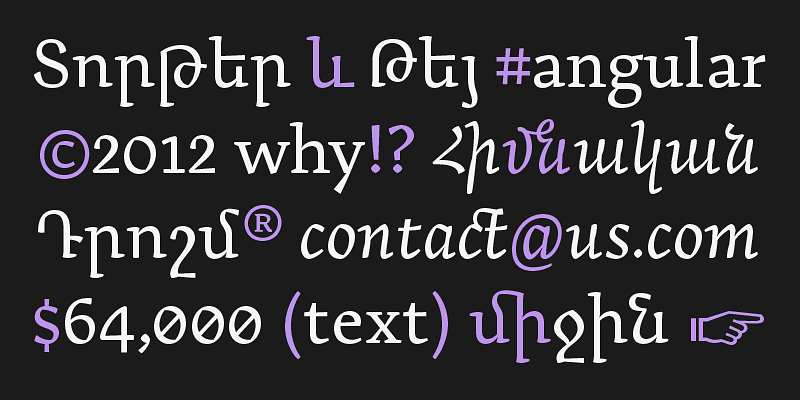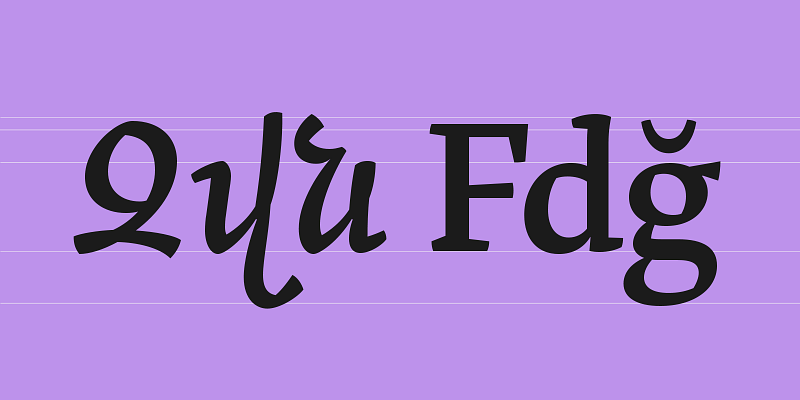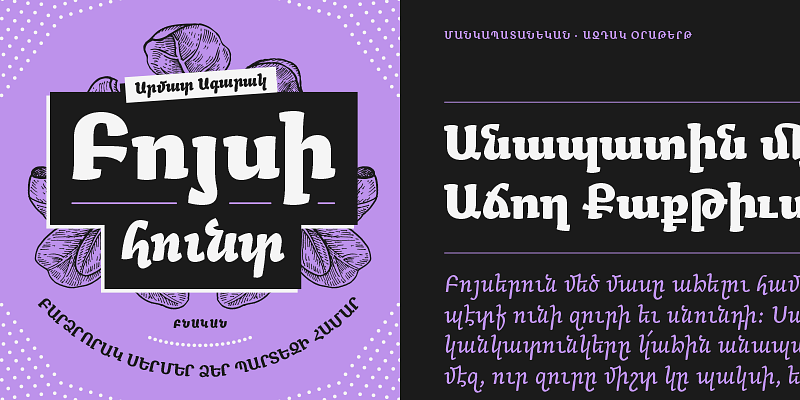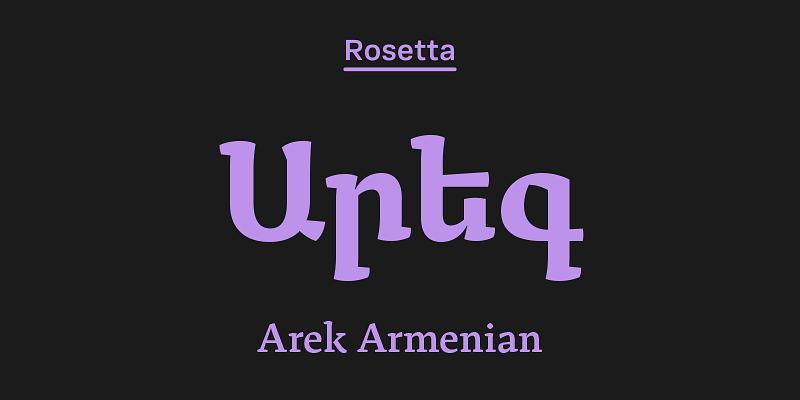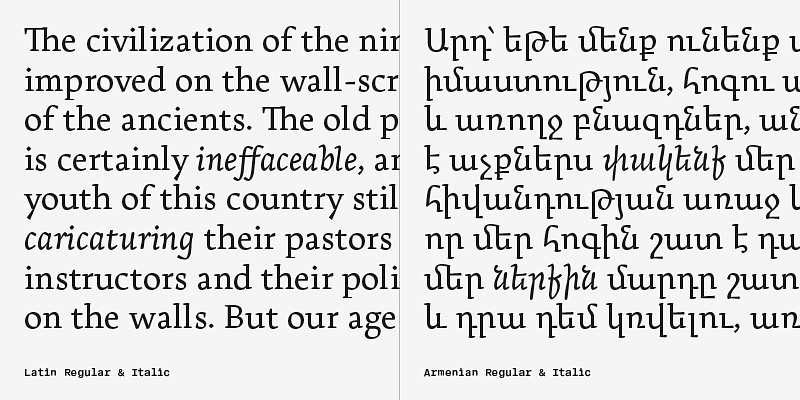
Arek ist eine leistungsstarke Sammlung von Schriftfamilien mit mehreren Strichstärken. Sie kombiniert eine klare, gut lesbare Hochkantschrift mit einer innovativen armenischen Kursivschrift und einer passenden lateinischen Schrift, die sich die Seite harmonisch teilen. Ursprünglich wurde Arek für Schulbücher entwickelt, aber auch bei allen anderen Projekten im redaktionellen Bereich zieht sie die Aufmerksamkeit der Leser auf sich.